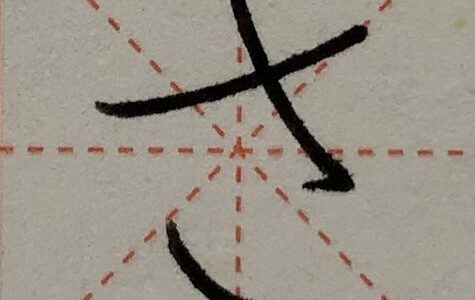
物事を上達させる為には、理論と実践が大切と言われていますね。
それは、ペン字の練習にも例外なく当てはまります。
理論=インプット
実践=アウトプット
という感じで進めていきます。
では、ペン字でいうインプットとアウトプットは何なのでしょうか?
今回は、この辺りのことを具体的に説明していければと思います^^
①ペン字における目標を決め、それを達成する手段をリサーチする(インプット)
子どもの頃は自身の可能性を広げる時間として、様々な事に取り組むことが大切で、
時間もたっぷりあるので気持ちの赴くままに練習しても良いと思います。
ただ、大人になると誰もが自由な時間を確保できるわけではありません。
限られた時間の中で、いかに最大限のパフォーマンスをするか、ということを念頭に置く必要があります。
ということで、何かを始める時は、闇雲に手を出すのではなく、最初にある程度見通しを立てて、着地点を決めておくと良いでしょう。
自分が立てた目標や前提がゴールになるように、物事は進んでいくからです。
第一に、自分は字をどのレベルまで引き上げたいのかを確認します。
趣味としてなのか、
それとも、資格を取ったり、今の仕事に生かしたりしたいのか
もしくは、講師となって活動していきたいのか…
こんな感じで、自分はどこを目標とするのか考えていきます。
第二に、独学で進めるのか、通信講座を受講するのか、実際に教室に通うのか決めます。
独学する方は、書店に行ってペン字練習用のテキストを購入します。
通信講座を受けたい人は資料請求して情報収集します。
教室に通いたい人は、見学や体験授業などを受けてみてください。
自分の定めた目標によって、必要な情報や集まってくる知識の量に差が出てくるので、この最初の段階が結構重要なのです。
②手本となる字のサンプルを集める(インプット)
①でどのような手段を選択しても、「自らの意志で能動的に学んでいく」という意識が大切です。
一口に「綺麗な字」と言っても、書いた人ごとに個性があるので様々な種類があります。
市販でもあらゆるペン字テキストが出版されていて、どれを選べば良いか分からないという方もいると思います。
個人的にお薦めしたいのは、江守賢治さんという方が監修したり執筆したりしている参考書やテキストです。
この方のテキストは講師の方々や、硬筆書写技能検定を受ける方達も重宝している程、美しい字と分かりやすい解説が載せられています。
これをベースにした上で、その他にも自分が好きな字、気になる字を見つけて参考にしていくのもアリだと思いますよ^_^
③②で集めたサンプルを観察する(インプット)
サンプル(手本)を集めてきたら、次は観察・分析をしていきます。
分析といっても、事細かくする必要は無いので安心してください^^
まずは、お手本をざっと眺める感じでOKです。
綺麗な字はどういうところが「綺麗」と認識されるのか、
字形や、縦画、横画はどんな書き振りなのか、
字の余白(隙間)はどうなっているのか…
などなど、自分が気付いたことを記憶したり、書き留めていってください。
④実際に書く練習をしてみる(アウトプット)
インプットしてきたことを踏まえて、お手本を横に置き、実際に書いてみます。
最初は手が震えて、線がブレてしまったり、字の骨格が歪んでしまったりすることもあると思います。
しかし、それは手首がペンの扱い方に慣れていないだけなので、何度も書いていくうちに上手く書けるようになってきます。
なかなか感覚が掴めない、という人はお手本の上に薄い紙を載せてなぞり書きするのも良いですね。
何度もなぞっているうちに、手が字形を覚えてくれますよ٩( ‘ω’ )و
⑤書いた字を手本と比較して改善点を見つける(インプット)
一通り書き終わったら、1人反省会を行います。
間違っても「何でこんなに下手なんだ〜、もうムリ(´༎ຶོρ༎ຶོ`)」
なんて、自分を責め過ぎないで下さいね。
自分を責める癖は、いずれ物事を諦める言い訳に使われるようになります。
字が上手くなりたいのであれば、劣等感に浸るのではなく、
何故自分の字がそうなってしまっているのか?
手本と自分の字の違いはどこなのか?
という事を、客観的に分析すれば良いだけなのです。
修正点が見つかれば、手本なり、自分の字なりに、メモしていってください。
自分の気づきを記録として残していくと、振り返ってみた時にすぐに思い出せて、練習に取り掛かりやすくなりますよ^ – ^
⑥改善点を踏まえて、もう一度書き直す(アウトプット)
もう一度書き直した字が、前回書いた字より綺麗になっていれば、あなたの着眼点は正しかったということです。
書き直して、イマイチ綺麗にならなかった場合は別の方法を探し直します。
仮説→検証という形で繰り返して練習してみて下さい。
⑦まとめ
さて、以上6つの過程を述べさせていただきました。
①〜⑥を繰り返すことで、上達していきます。
こうして見ると、字の練習は科学分野と共通する部分が多々あるように思いますね。
綺麗な字を追求する過程で生まれた下手な字はレベルアップする為に必要な資料となります。
どんな字からも学びを得て、上達に繋げていきましょう。